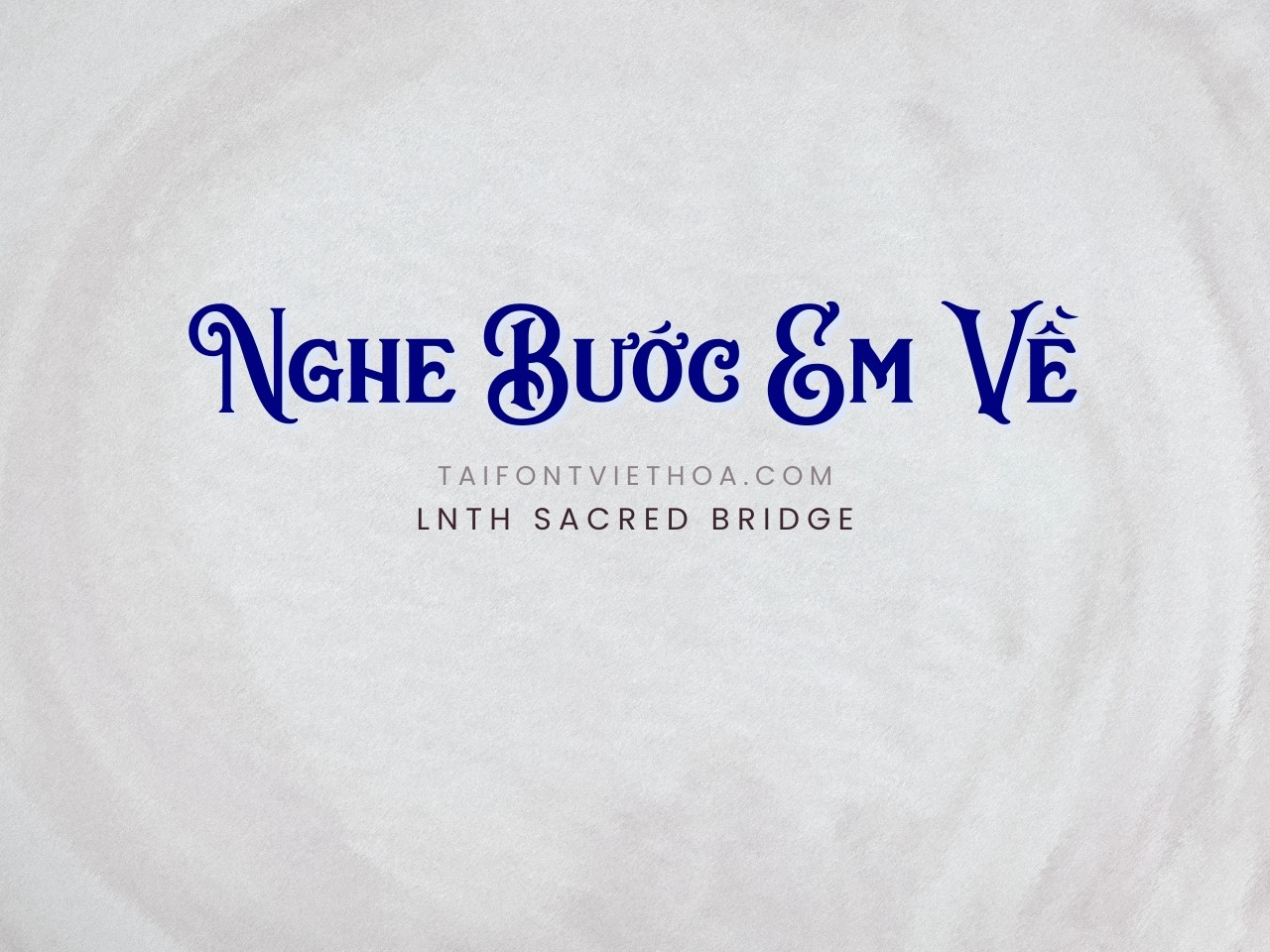
Font việt hóa LNTH Sacred Bridge
Tác giả Font: Bombastype
Giới thiệu về font LNTH Sacred Bridge – Cây cầu thiêng liêng giữa cổ điển và hiện đại
LNTH Sacred Bridge là font serif cao cấp được Việt hóa từ thiết kế gốc của Bombastype – một nhà thiết kế nổi tiếng với phong cách hoài cổ pha lẫn hiện đại. Font sở hữu cấu trúc trang trọng, thanh lịch với các chân chữ sắc sảo, gợi nhớ đến những bản in sách cổ hoặc tạp chí nghệ thuật thời kỳ đầu thế kỷ 20. Phiên bản Việt hóa do Tuỳn Pucca thực hiện, hỗ trợ đầy đủ tiếng Việt cùng hơn 60 ngôn ngữ khác trên toàn cầu.
Đặc điểm thiết kế và ứng dụng của font LNTH Sacred Bridge
Font có cấu trúc serif điển hình với tỷ lệ chữ thanh mảnh, độ tương phản nét dày mảnh hợp lý và các đường bo tinh tế ở đầu nét chữ. Thiết kế tổng thể gợi cảm giác cổ điển nhưng vẫn giữ được sự tối giản hiện đại, rất phù hợp cho các tiêu đề, tên thương hiệu hoặc thiết kế in ấn cần độ tin cậy và thẩm mỹ cao.
Font phù hợp với các ngành như bất động sản, công nghệ, thiết kế nhận diện thương hiệu, giáo dục, mỹ phẩm cao cấp hoặc nội dung xuất bản. Các ứng dụng nổi bật gồm: thiết kế sách, tạp chí, bao bì, tiêu đề web, logo cao cấp hoặc các sản phẩm mang tinh thần sang trọng và lịch lãm.